Projeto fotográfico “Favelagrafia” cria tipografia usando fotos tiradas nas favelas cariocas
Com um iPhone nas mãos, os moradores produziram fotos incríveis
A visão estereotipada das favelas do Rio de Janeiro é problemática: ela virou sinônimo de carência, tráfico e perigo. Para mudar essa visão, o projeto Favelagrafia, lançado como exposição na semana passada, colocou nas mãos dos moradores de várias favelas cariocas um iPhone e pediu que eles registrassem sua realidade.
Um morador de cada uma das comunidades do Alemão, Santa Marta, Prazeres, Rocinha, Babilônia, Mineira, Providência e Cantagalo tiraram fotos. O principal intuito é a busca por diferentes perspectivas daqueles que vêem o mundo do outro lado, retratando a realidade dos locais de forma verdadeira e pouco óbvia. As fotos foram tiradas desde junho deste ano.
Para divulgar o projeto, algumas das obras produzidas pelos moradores passaram por um tratamento de design gráfico, criando interessantes tipografias que futuramente estamparão cartazes, postais e camisetas. Você pode conferir algumas abaixo no topo do post e abaixo.
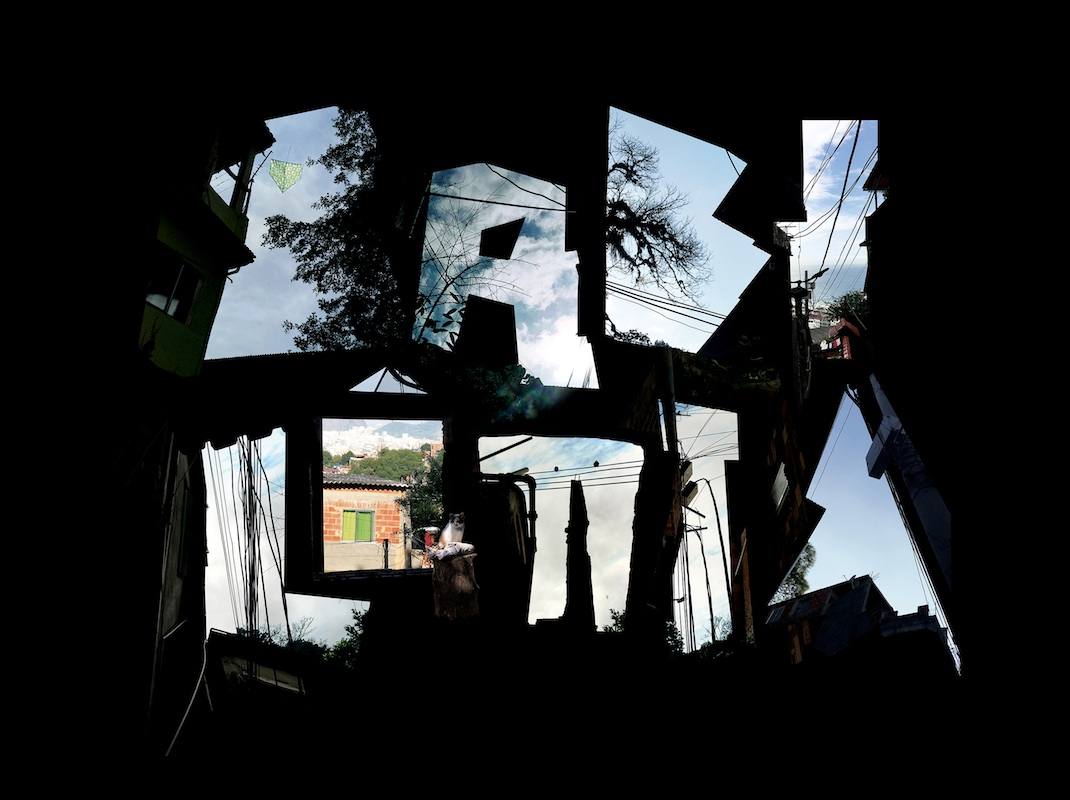
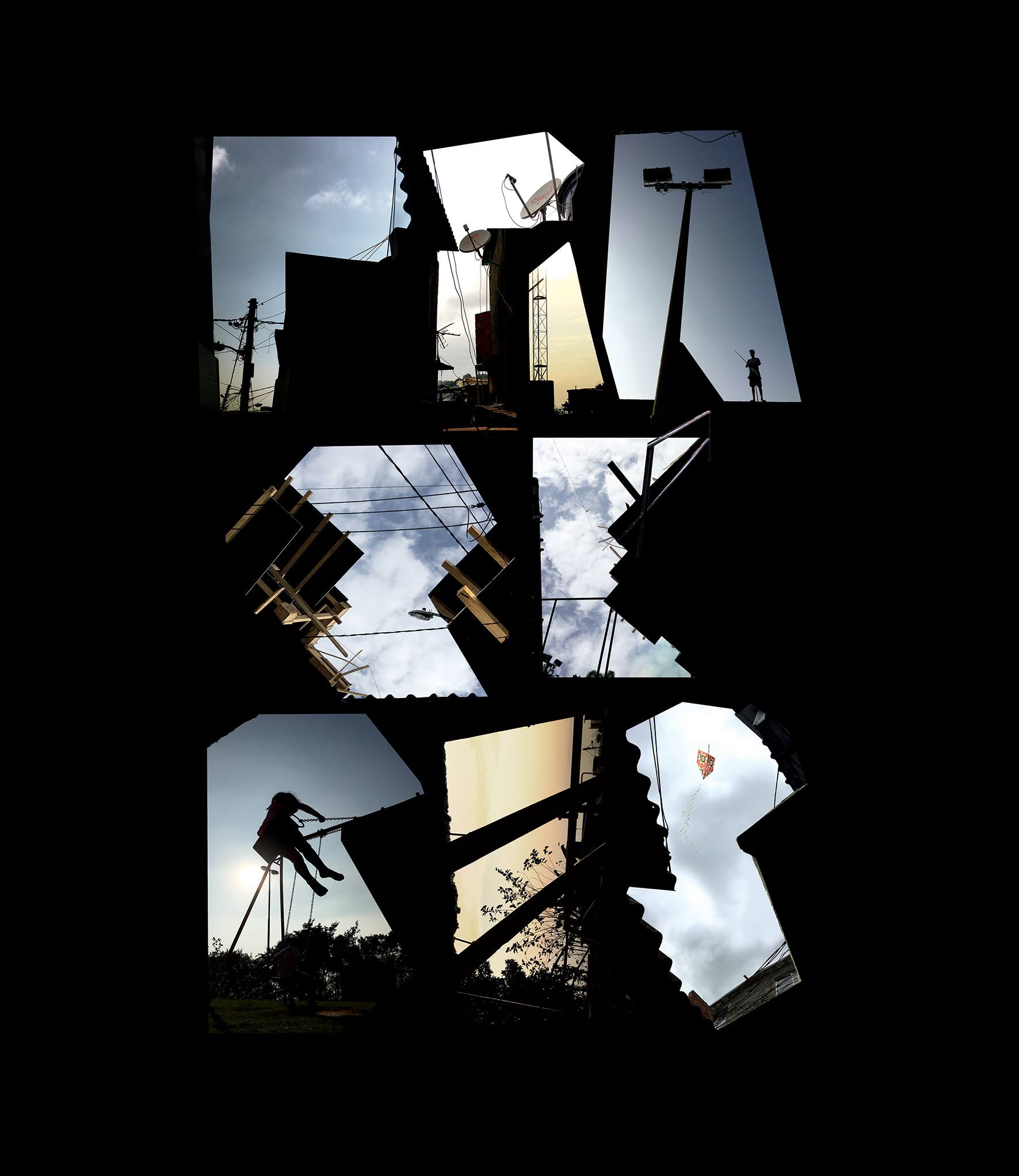
Grande parte do senso comum acredita que a fotografia é feita unicamente de belas paisagens, do que é perfeito, mas no projeto vemos que o inesperado, o concreto em contato e a periferia também podem ser belos e contar interessantes histórias.
Segundo Karina Abicalil, idealizadora do projeto junto com André Havt, inicialmente foi criado um perfil do Instagram do projeto que foi alimentado com as fotos a medida que elas iam sendo tiradas. Apenas agora foi criada a exposição, site e o livro. Aliado a isso, os moradores também estão fazendo um curso do Sebrae para desenvolverem mais suas habilidades fotográficas e a exposição pode ir até para fora do país.
Vale a pena conferir todas as fotos do projeto, que por sinal ficaram excelentes, no próprio site do Favelagrafia. Elas também estão expostas desde a semana passada e até o dia 4 de dezembro no Museu de Arte Moderna no Rio de Janeiro e em um livro.
As agências NBS Rio+Rio e ISL foram responsáveis pela realização do projeto enquanto a agência Tundra Studies
ficou por conta das tipografias.